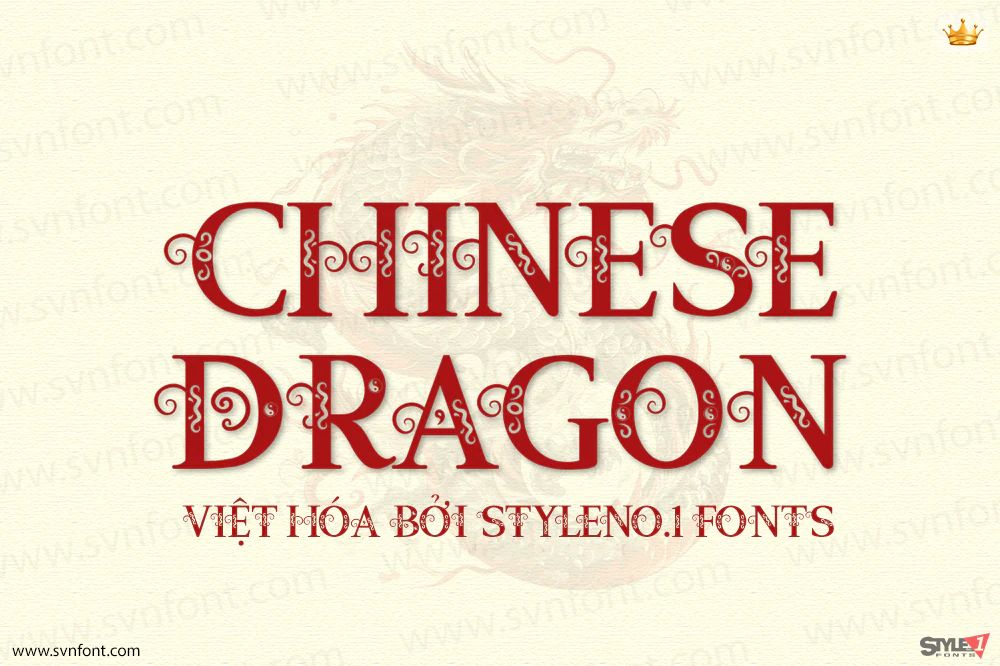
Chinese Dragon là một font chữ hiển thị phong cách Trung Hoa hiện đại, sở hữu diện mạo trang trí độc đáo và thu hút. Đây là biến thể của dòng font decorative lấy cảm hứng từ chủ đề Trung Quốc. Không chỉ đơn thuần là những ký tự thông thường, kiểu chữ này còn thể hiện rõ nét tinh thần và sắc thái văn hóa Trung Hoa.
Font được tạo ra nhằm phục vụ cho nhiều dịp lễ hội và sự kiện. Nó rất phù hợp để sử dụng trên poster và banner cho các dịp như Tết Nguyên Đán, banner chào mừng hoặc poster chủ đề tiệc dành cho khách mời. Chinese Dragon cũng có thể ứng dụng cho áo thun, bìa sách và branding. Font phù hợp cho mọi sản phẩm mang chủ đề Trung Hoa.